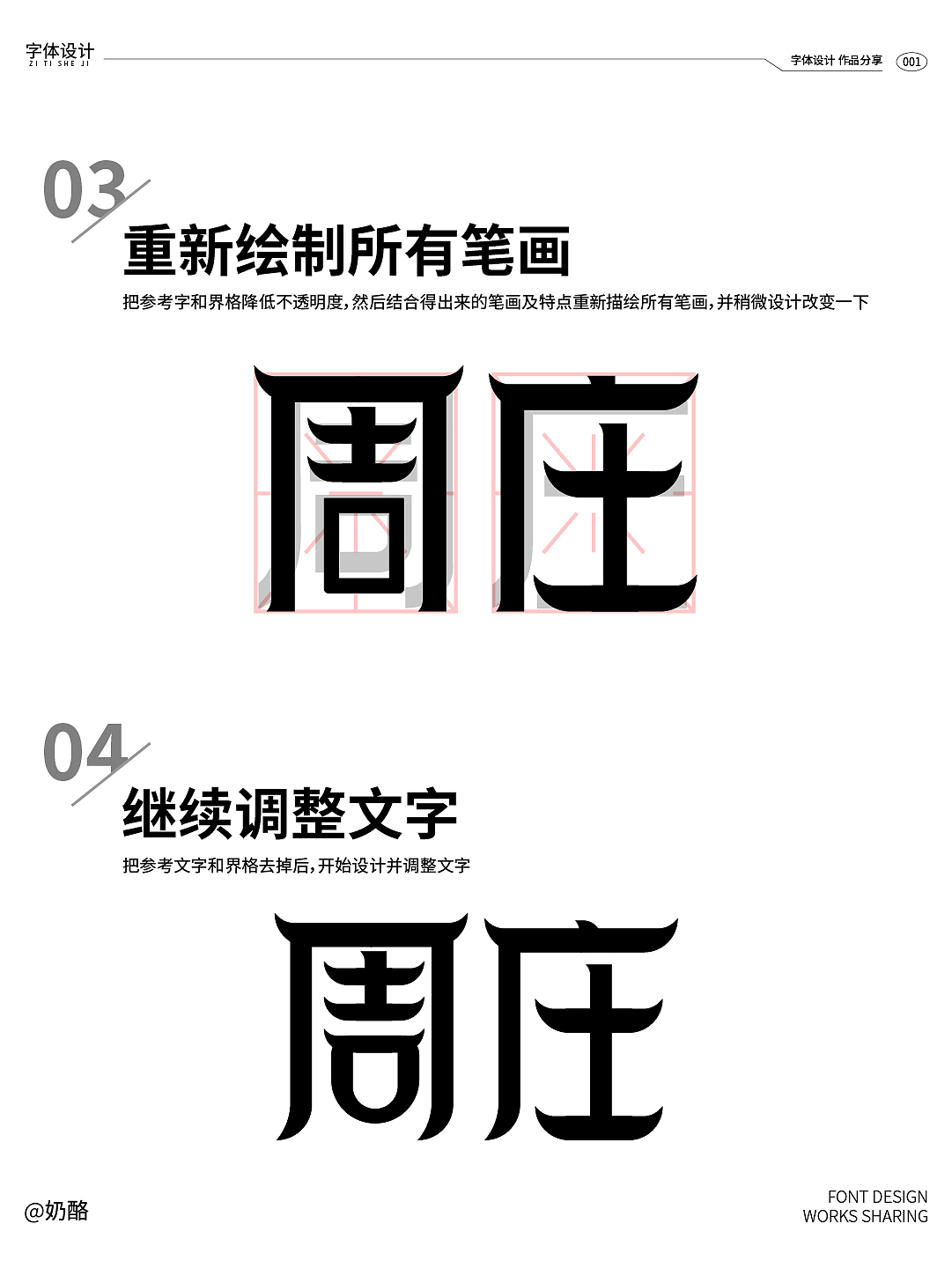
字体设计案例分享
这种标题字体是如何设计的呢?
第一步:寻找参考字体
在系统中挑选一款你认为合适的字体,作为后续设计的参考字形。
第二步:提取古镇元素
选取一张古镇图片,使用钢笔工具勾勒出屋檐等特色结构,将其转化为字体中的横、竖等基本笔画。
第三步:重新绘制笔画
将参考字与界格的不透明度降低,结合已提取的古镇元素与笔画特点,重新绘制所有笔画,并适当进行造型调整。
第四步:精细调整字形
移除参考文字和界格,专注于字形的整体设计与细节优化,确保风格统一且富有特色。
第五步:完成文字排版
将最终设计好的文字进行合理排版,呈现完整的视觉效果。